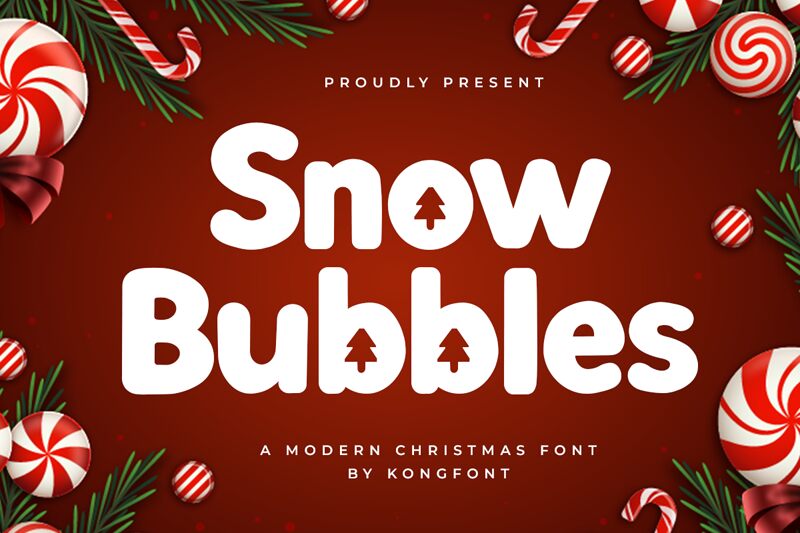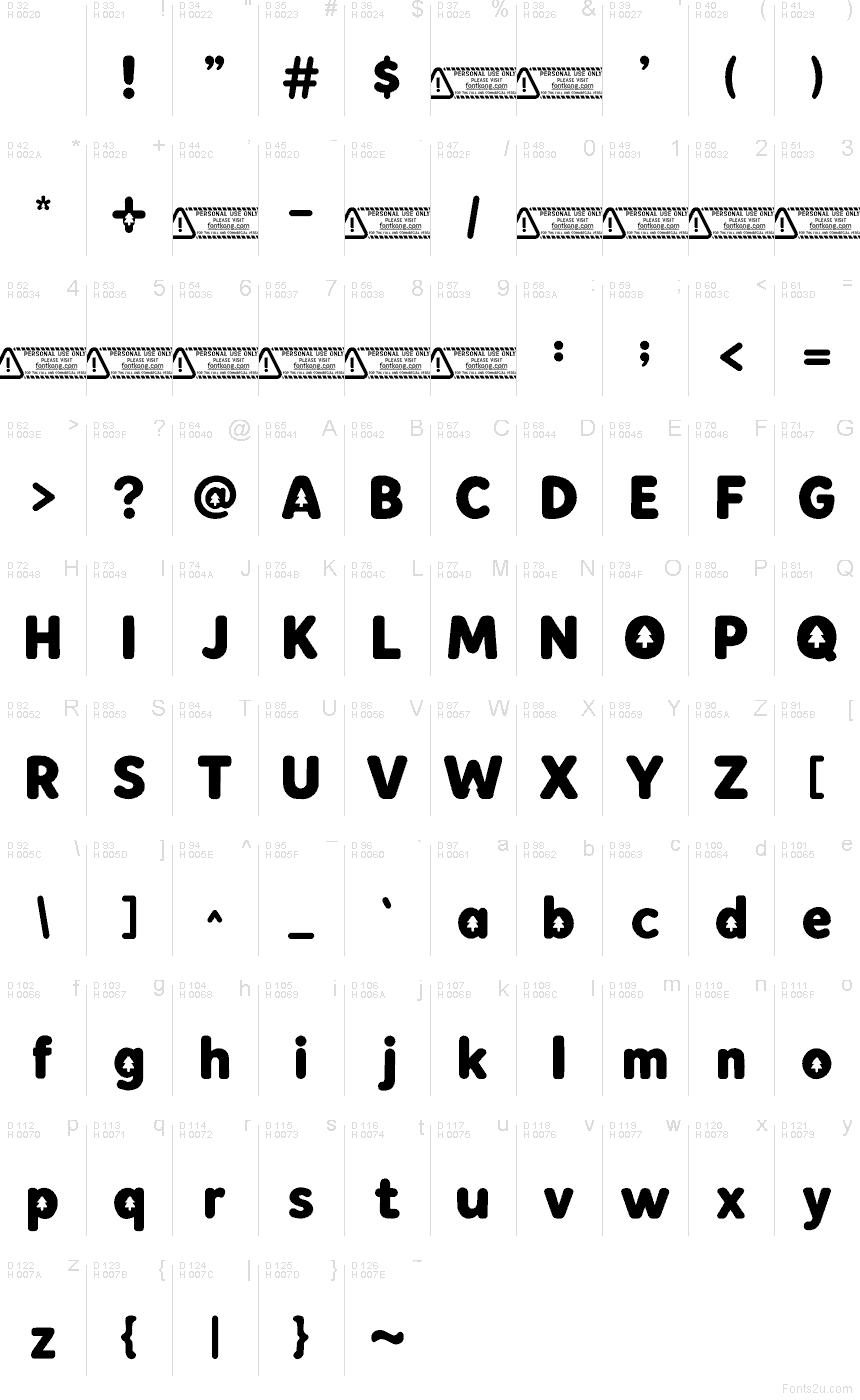
Snow Bubbles od Kong Font je bezplatné vianočné písmo typu display so zaoblenými, bublinovými písmenami a motívom stromčeka ukrytým v jednom zo znakov. Mäkké hrany a priateľský, „nafúknutý“ vzhľad dodávajú nápisom sviatočný a hravý charakter bez potreby ďalších ozdôb.
Snow Bubbles sa skvele hodí na vianočné pohľadnice, sezónne plagáty, menovky na darčeky, pozvánky, slávnostné logá a bannery na sociálnych sieťach. Vďaka zaobleným tvarom a jednoduchému motívu sa hodí do návrhov, ktoré vyžadujú veselý vianočný detail namiesto formálneho písma.